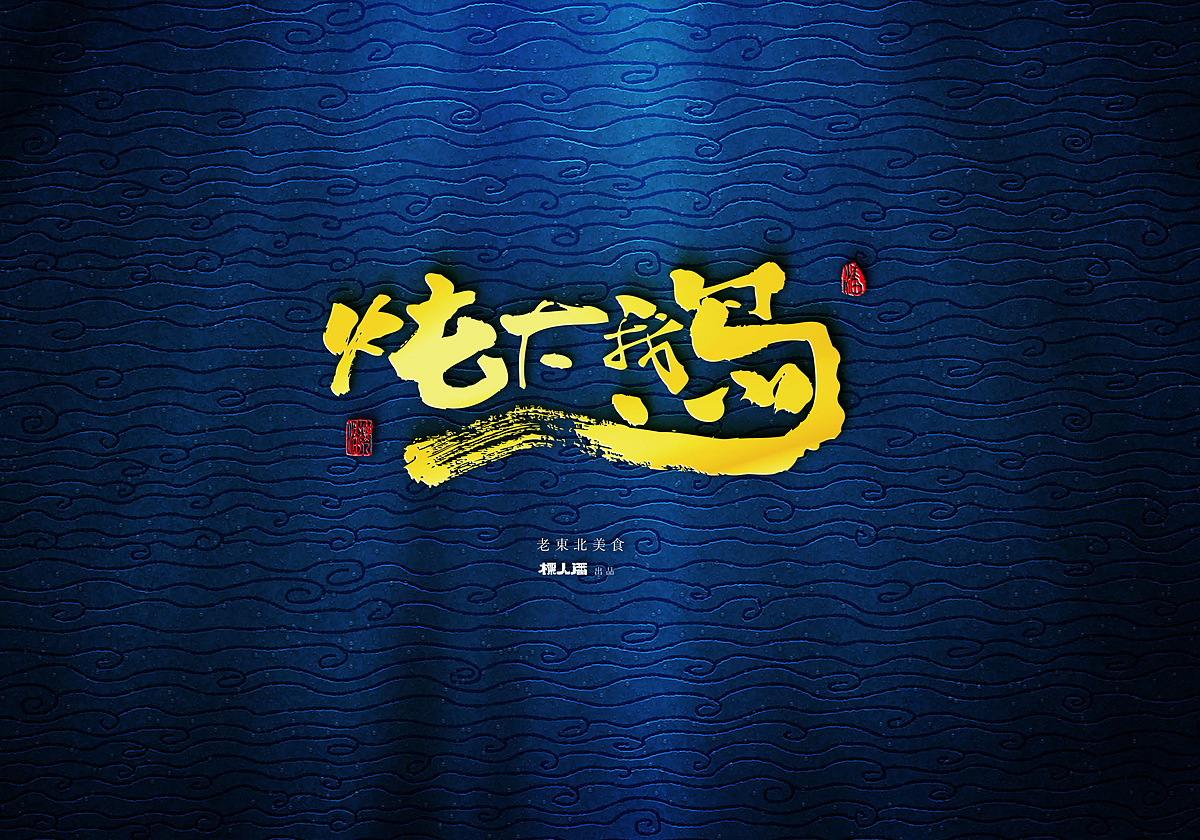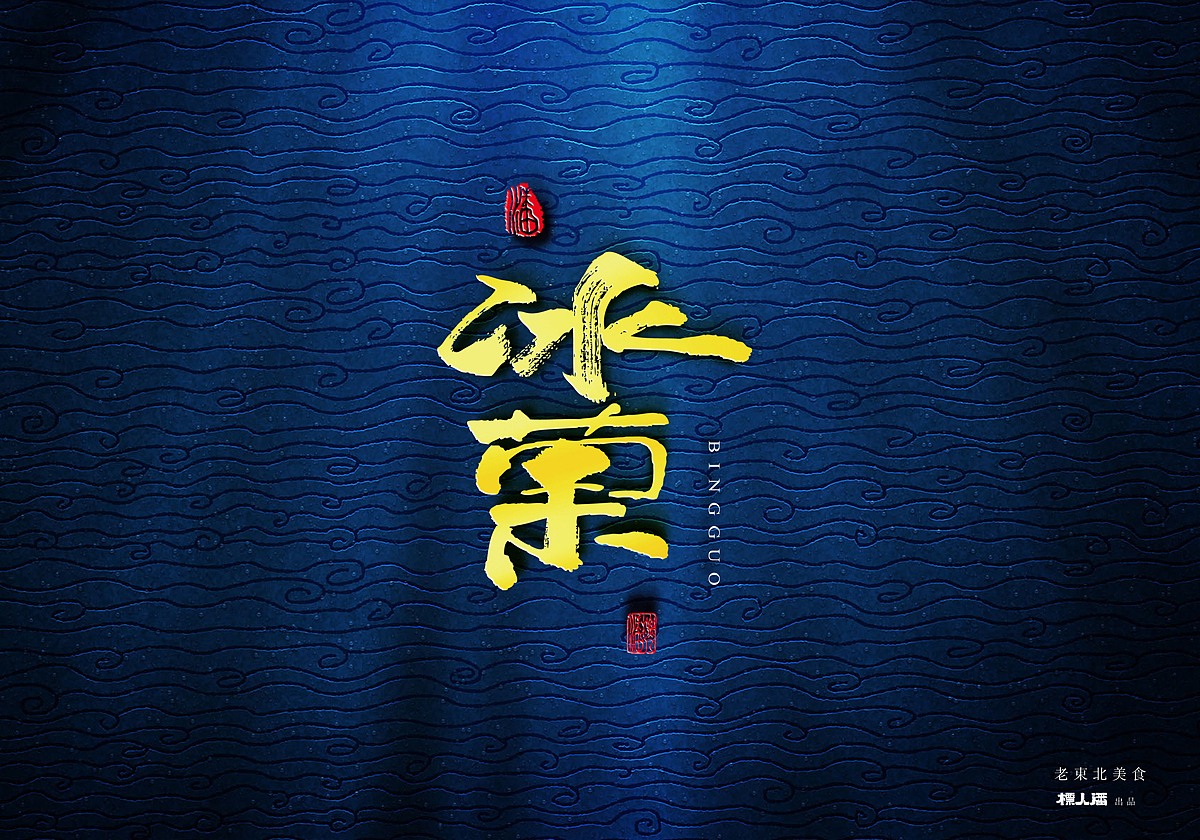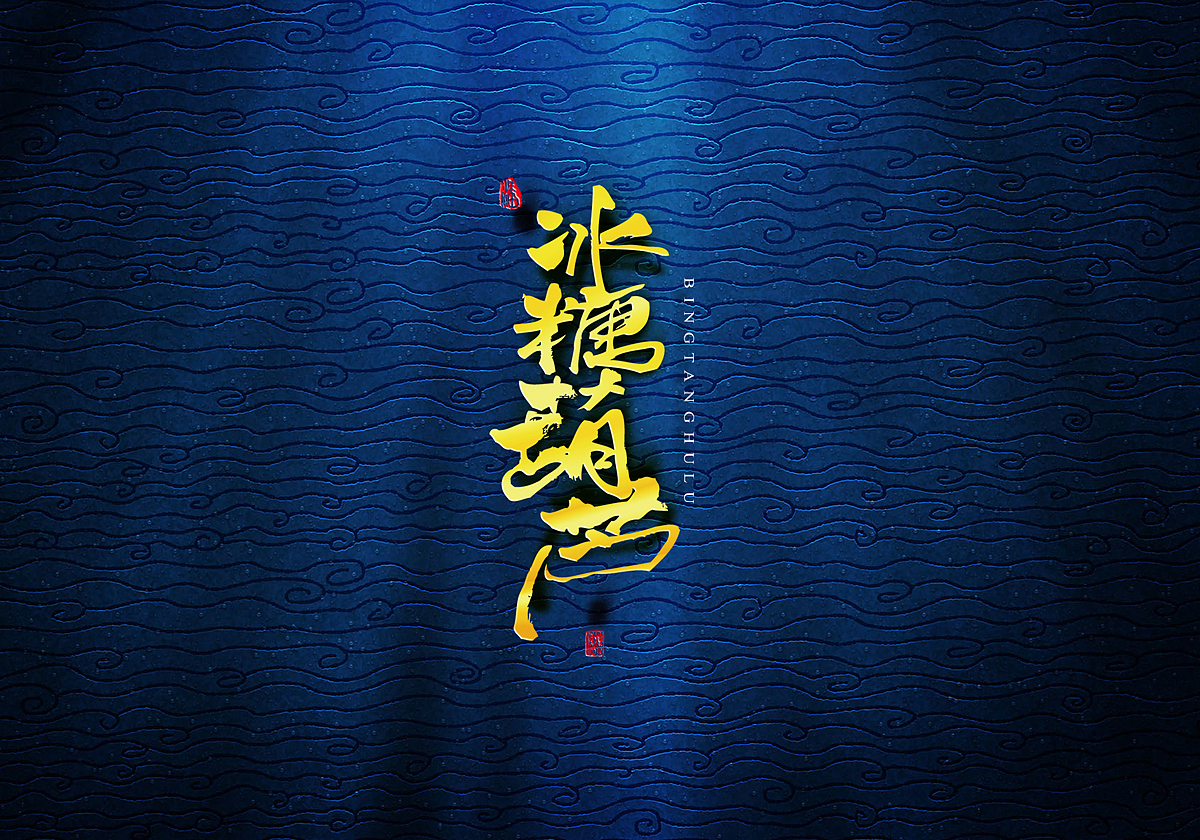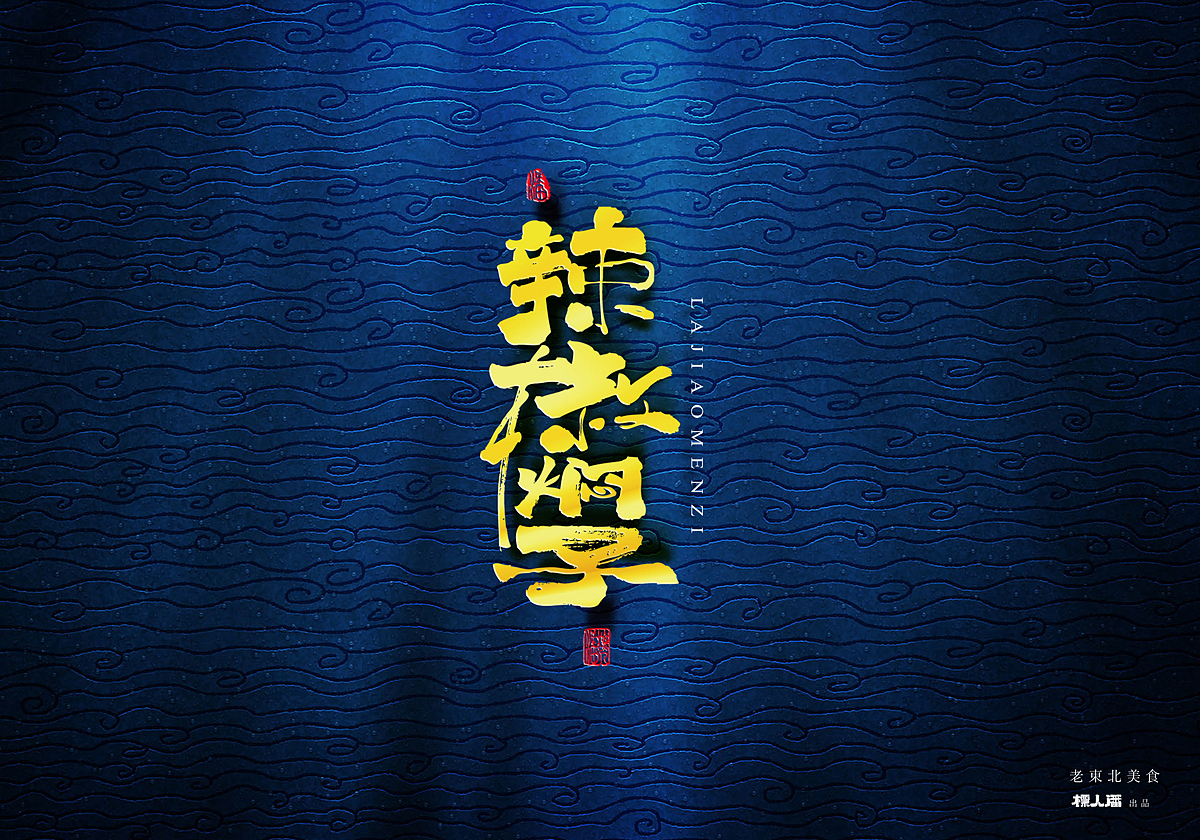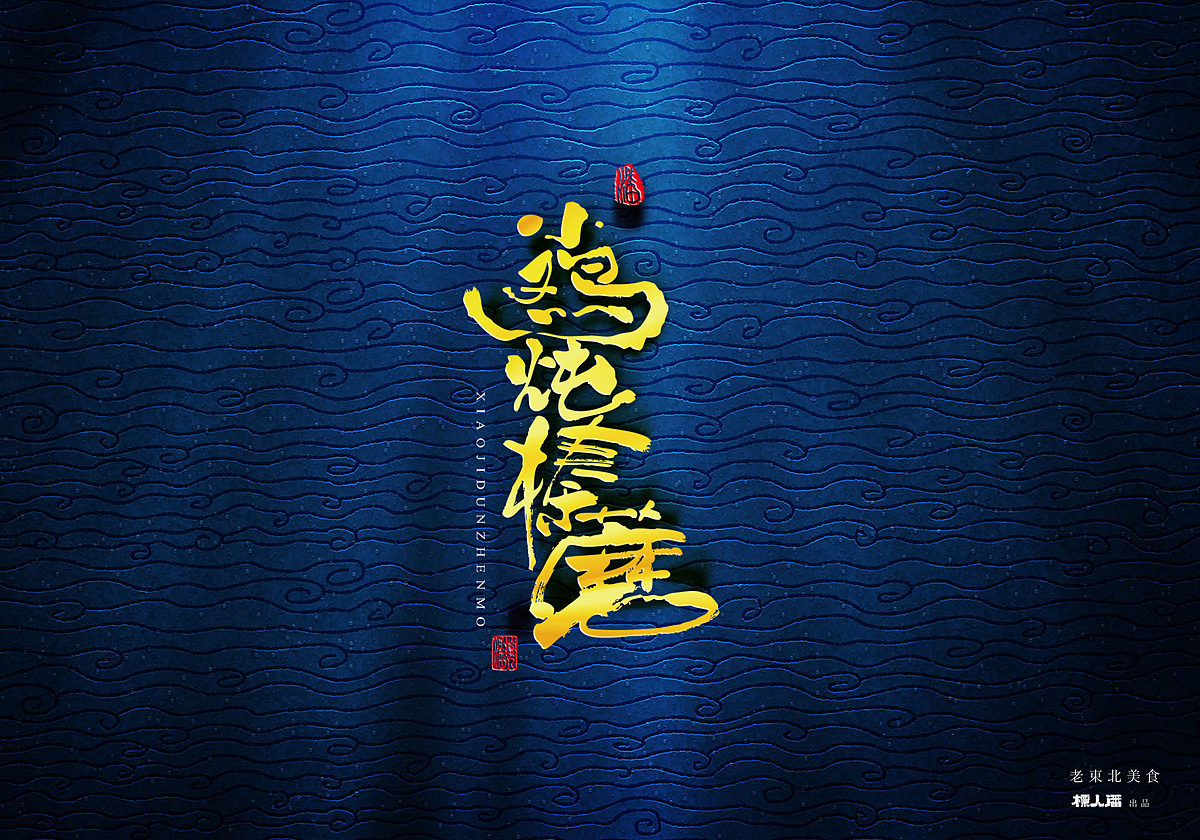
传统美食系列之东北美食(升级版)
儿时的记忆全在东北这片热土
每一个美食的味道都那么记忆犹新
我们老祖宗留下的传统技艺和美食需要继承和发扬
当然更加是扎心的回忆
再此之际,本人拟做一个系列,写出每个地方传统美食,给大家一个回忆吧
书法字体乃是传统精华之髓
之前上传了一个未加修饰的版本
在视觉上可能不能很好的表达
故上传这一升级版